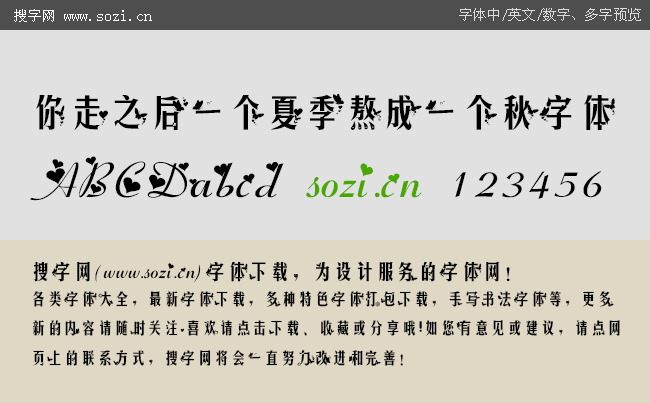
你走之后一個夏季熬成一個秋字體
搜字網(wǎng)給大家提供一款你走之后一個夏季熬成一個秋字體手機(jī)中文字體下載。這款手機(jī)字體是在姚體字體筆畫間插入了漂亮的卡通心形與蝴蝶等圖案。即有姚體雋秀工整,整齊劃一的風(fēng)格,又有增添了趣味性,特別適合喜歡手機(jī)字體個性一些的朋友在手機(jī)上安裝使用。